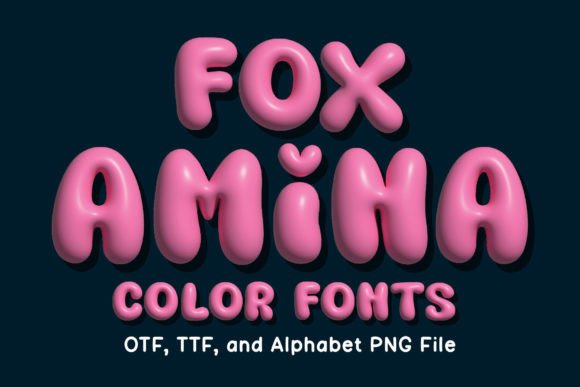
Fox Amina
適切なデザイン要素を見つけるのは難しい場合がありますが、Fox Aminaは作品を即座に引き立てる優れたコレクションを提供します。
精密に作られたFox Aminaは、クリーンなベクター、滑らかなタイポグラフィ、そして安心のための商用ライセンスを提供します。
POD(オンデマンド印刷)製品、結婚式の招待状、またはソーシャルメディアのグラフィックを作成している場合でも、Fox Aminaは理想的です。